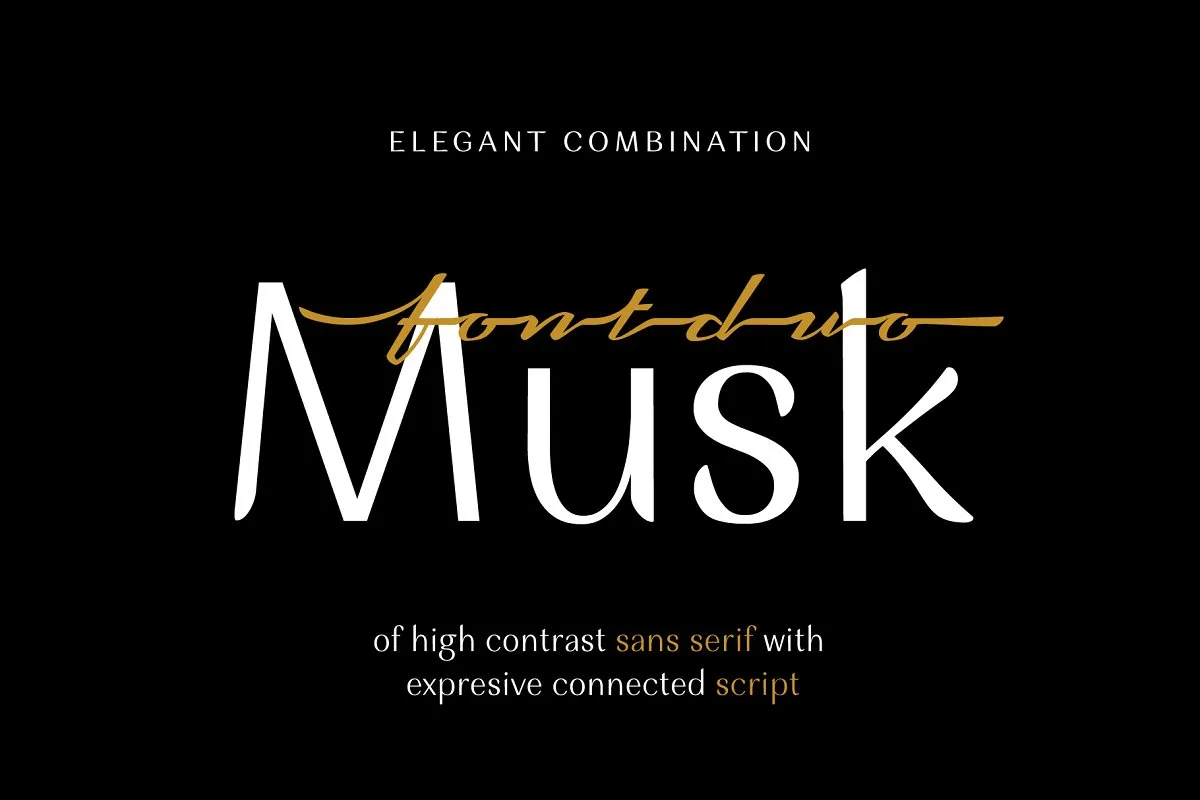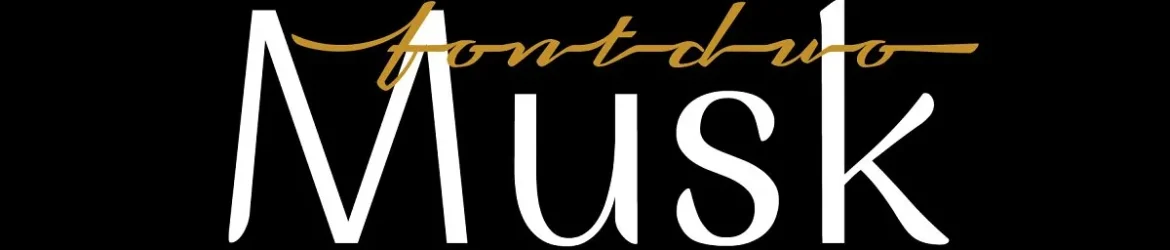
Musk Sans Serif Typeface – Download Grátis
Introduzimos a nova fonte Musk Sans Serif para vocês hoje. Inspirada na melhor qualidade do aroma intenso e delicado que é o musk, essa fonte combina elegância com uma serif alta de contraste, misturando formas de script expressivo e conectadas. A serif sem serif contém três pesos: regular, médio e bold, para uso tanto em exibição quanto para texto. Cada caractere mostra variações únicas das formas, especialmente nos terminais, com o objetivo de manter a legibilidade e a clareza. Além disso, esta serif também oferece três pesos: regular, médio e bold para uso tanto no display quanto em texto do corpo. Musk Sans Serif tem mais de 240 caracteres diferentes, perfeitamente adequada para um amplo range de aplicações.